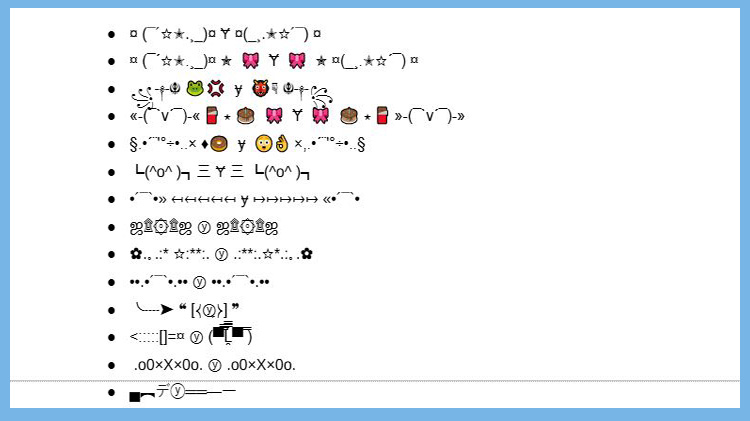
Tuyển chọn 100+ kí tự đặc biệt chữ Y sáng tạo nhất
Kí tự đặc biệt chữ Y là những biến thể sáng tạo của chữ cái thông thường, giúp bạn tạo ra phong cách riêng biệt trên mạng xã hội. Những kiểu chữ này có thể bao gồm chữ cái cách điệu, kí tự Unicode hoặc các kiểu chữ trang trí độc lạ. Dưới đây là danh sách các dạng kí tự chữ Y độc đáo mà Mobifonts chia sẻ. Đừng bỏ lỡ nhé!
Những kí tự đặc biệt chữ Y phổ biến thường được dùng để đặt tên hoặc tạo phong cách riêng. Chúng có thể là các dạng chữ có nét thanh mảnh, cách điệu hoặc mang dấu hiệu đặc biệt. Một số mẫu thường gặp:
Nếu bạn đang tìm kiếm những mẫu chữ Y kí tự đặc biệt ấn tượng, dưới đây là những kiểu chữ sáng tạo nhất giúp làm nổi bật tên hiển thị của bạn. Dù bạn muốn một phong cách mạnh mẽ, cá tính hay nhẹ nhàng, tinh tế, những kí tự đặc biệt này sẽ giúp bạn tạo dấu ấn riêng biệt.
Những kí tự này thường được sử dụng trong các văn bản nghệ thuật hoặc khi tạo tên người dùng trên tất cả nền tảng.
Chữ Y in hoa,không chỉ giúp tên hiển thị của bạn trở nên nổi bật mà còn tạo ấn tượng mạnh mẽ trên các nền tảng. Bạn có thể sử dụng chúng để thể hiện phong cách cá nhân, tạo điểm nhấn cho nickname hoặc thậm chí kết hợp với các biểu tượng đặc biệt để tạo ra một thiết kế sáng tạo và độc đáo hơn.
Những chữ kiểu này giúp tên hiển thị trông mạnh mẽ, sang trọng và thu hút hơn.
Những kí tự chữ Y đặc biệt viết thường không chỉ mang lại vẻ đẹp thanh thoát mà còn giúp bạn tạo dấu ấn riêng một cách tinh tế. Dù bạn sử dụng để đặt tên trong game, làm chữ ký cá nhân hay trang trí nội dung trên mạng xã hội, những kiểu chữ Y này chắc chắn sẽ khiến mọi ánh nhìn bị thu hút.
Chữ Y lộn ngược không chỉ mang lại sự mới lạ mà còn giúp tên hiển thị của bạn trở nên độc đáo và thu hút hơn. Nếu bạn muốn tạo điểm nhấn hoặc đơn giản là muốn gây ấn tượng với bạn bè, thì đây chắc chắn là lựa chọn không thể bỏ qua.
Kí tự đặc biệt chữ Y viết ngang không chỉ tạo điểm nhấn độc đáo mà còn giúp tên hiển thị của bạn trông phá cách và ấn tượng hơn. Đây là sự lựa chọn tuyệt vời cho những ai muốn nổi bật trong các nền tảng.
Unicode cung cấp nhiều biến thể kí tự chữ Y kiểu độc đáo, phù hợp với nhiều nhu cầu sử dụng khác nhau. Dù bạn muốn tạo dấu ấn riêng trong tên hiển thị trên mạng xã hội, Unicode đều có giải pháp hoàn hảo. Với những kí tự này, bạn không chỉ thể hiện cá tính mà còn tạo ra điểm nhấn đặc biệt, giúp nội dung của bạn trở nên bắt mắt và thu hút hơn.
Những kí tự này có thể được sử dụng trên nhiều nền tảng mà không bị lỗi hiển thị.
Chữ Y cách điệu không chỉ giúp tên hiển thị của bạn trở nên nổi bật mà còn thể hiện phong cách riêng, cá tính độc nhất. Dù bạn đang tìm kiếm một kiểu chữ mạnh mẽ, mềm mại hay phá cách, những kí tự đặc biệt chữ Y sẽ giúp bạn sáng tạo không giới hạn.
Bạn có thể kết hợp các kí tự này với các biểu tượng khác để tạo hiệu ứng đặc biệt hơn!
Mọi thắc mắc về các kiểu chữ Y sẽ được giải đáp qua các câu hỏi sau đây:
Hầu hết các kí tự Unicode đều có thể hiển thị tốt trên tất cả các nền tảng trực tuyến.
Hoàn toàn có thể! Bạn có thể thêm các biểu tượng để làm nổi bật hơn.